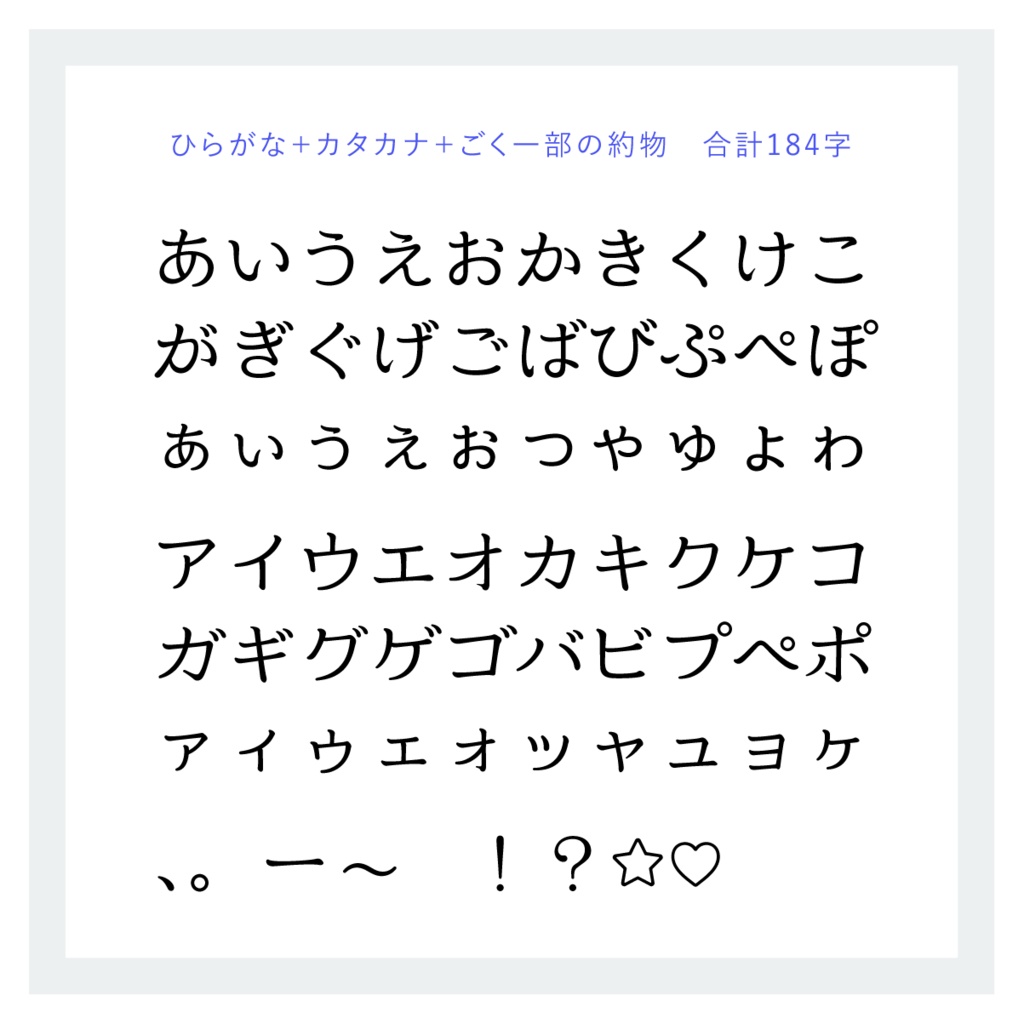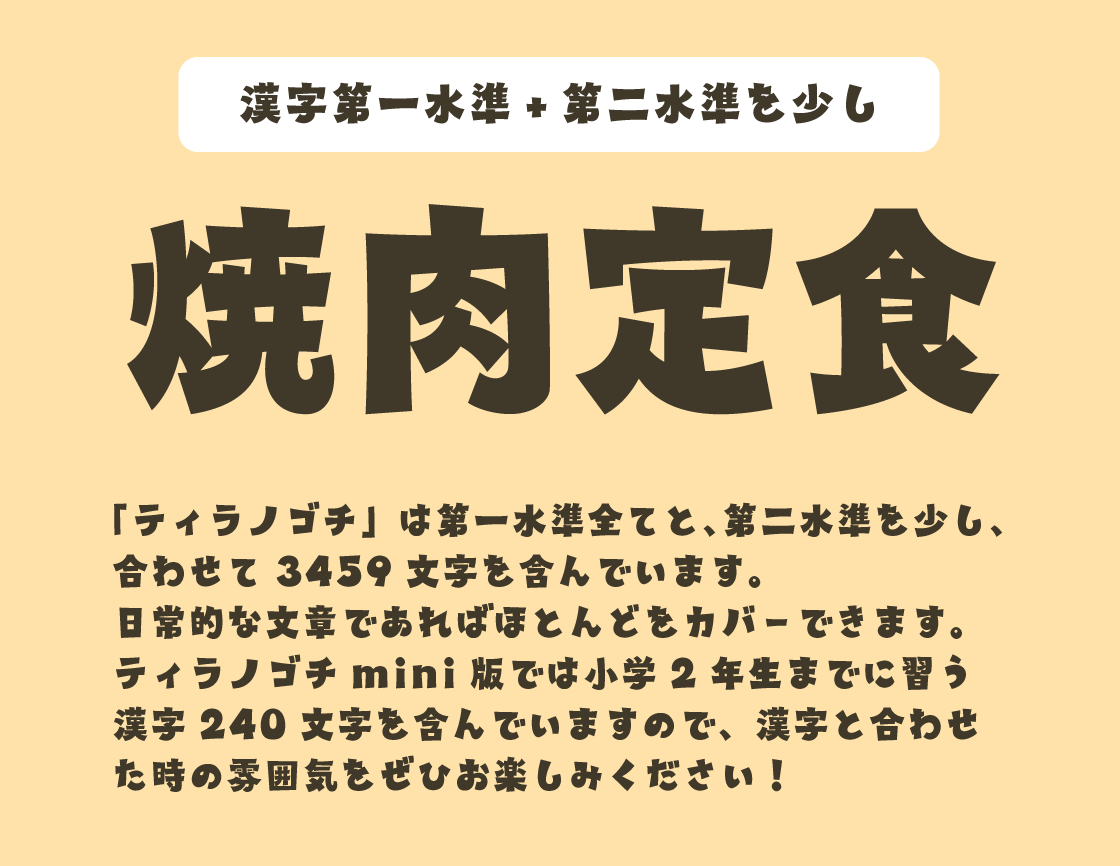
くすくすあめ
「くすくすあめ」は、昨年12月に公開されたばかりの比較的新しいフォントです。
シンプルながら手書きっぽさも感じられる丸ゴシック体フリーフォントとなっており、均一な線と優しい丸みが特徴で、やわらかな雰囲気を演出したいデザインに最適です。
スタイルに癖がないので、どのような場面でも使用しやすいフォントです。
| スタイル・ベース | 手書き風丸ゴシック |
| 収録内容 | ひらがな、カタカナ、漢字、数字、アルファベット、一部の記号 |
MPRばるーん
「MPRばるーん」は、M PLUS Rounded(M+)というオープンライセンスを使用したフォントです。今年の1月に公開されたばかりの新しいフォントとなっています。
幼稚園や保育園、学校だより、子ども向けの資料などにもぴったりなフォントです。風船の形は自動で決まるようです。
| スタイル・ベース | ポップ |
| 収録内容 | ひらがな、カタカナ、数字、アルファベット、一部の記号 |
はにはにフォント
「はにはにフォント」は、昨年8月に公開された手書きフォントです。ひらがな、カタカナ、数字、アルファベットが収録されています。フォントがとても可愛いので、漢字が含まれていないのが非常に残念です。
手紙風のデザイン、女性向けのランディングページ(クリエイティブ制作)にもぴったりで、個人的には手書きスタイルのなかでもイチオシのフォントです。
| スタイル・ベース | 手書き |
| 収録内容 | ひらがな、カタカナ、数字、アルファベット |
みそら明朝
「みそら明朝」は、「見やすさとかわいらしさ」を兼ね備えた明朝体フォントです。デザイン性と使いやすさのバランスが取れたスタイルとなっています。
| スタイル・ベース | 明朝 |
| 収録内容 | ひらがな、カタカナ、一部の約物・記号 |
りんごひめ(無料版)
「りんごひめ」は、レトロでキュートな雰囲気を持つシンプルかつデザイン性の高いフォントです。
無料版ではレギュラーウェイトのみが提供され、有料版にはボールドも含まれています。懐かしさと可愛らしさを演出したい場面に最適な書体です。
| スタイル・ベース | 手描き風レトロ |
| 収録内容 | ひらがな、一部記号 |
あおさぎ
「あおさぎ」は、デザイン性と実用性を兼ね備えた明朝体フォントです。豊富な文字数を収録しながら、商用利用可能で無料という特徴があります。
見出しやロゴデザインにも適しており、インパクトのある表現を可能にします。
| スタイル・ベース | 明朝 |
| 収録内容(無料版) | ひらがな、カタカナ、漢字、数字、アルファベット、記号、約物 |
ティラノゴチ(無料版)
「ティラノゴチ」は、やんちゃ小僧をイメージした、かわいらしさと力強さを兼ね備えたフォントです。遊び心のあるデザインで、個性的な表現を求める方に最適。
mini(無料)版は横書きのみとなっています。
| スタイル・ベース | 手書き |
| 収録内容(無料版) | ひらがな、カタカナ、漢字240文字 |
ぱぐのみんちょ(無料版)
「ぱぐのみんちょ」は、パグをモチーフにした愛嬌たっぷりの日本語フォントです。丸みを帯びた有機的なシルエットが特徴で、デザインにに温かみと可愛らしさを演出します。
mini(無料)版は横書き専用です。
| スタイル・ベース | 明朝 |
| 収録内容(無料版) | ひらがな、カタカナ、漢字80文字 |
にくまるフォント
「にくまるフォント」は、丸みを帯びた優しい印象の文字デザインが特徴です。ひらがなも漢字も柔らかな曲線で構成され、親しみやすさと可愛らしさを感じられます。
太めの字体で、温かみのある雰囲気を醸し出すのに適しています。細めより太めのフォントを探されている方にもぴったりです。
| スタイル・ベース | ベースはM+のためゴシック体に近い |
| 収録内容(無料版) | ひらがな、カタカナ、漢字、数字、アルファベット、記号 |
ふわふで
「ふわふで」は、やわらかい筆致が特徴の可愛らしい毛筆フォントです。
墨のにじみ感と丸みを帯びた文字形が、温かみのある和風デザインとなっていて、女性向けの和テイストな制作物に最適です。
| スタイル・ベース | 手書き |
| 収録内容(無料版) | ひらがな、カタカナ、数字、アルファベット |
ふわもこフォント
「ふわもこフォント」は、雲のような柔らかな印象の可愛らしい書体です。白抜きデザインが特徴的で、親しみやすさと高いデザイン性を兼ね備えています。
温かみのある雰囲気を演出するのに適したフォントです。
| スタイル・ベース | 手書き |
| 収録内容(無料版) | ひらがな、カタカナ、数字、アルファベット |
クラフト明朝
「クラフト明朝」は、手書き風の味わいある明朝体フリーフォントです。程よいかすれが特徴的で、温かみのある雰囲気を演出します。
第一水準漢字まで収録され、個人・商用利用も可能な実用性の高いフォントです。
| スタイル・ベース | 手書き |
| 収録内容(無料版) | ひらがな、カタカナ、漢字、数字、アルファベット、約物 |
錦的ポップ体
「錦的ポップ体」は、YouTubeなどの動画テロップにも最適なフリーフォントです。
実際に使用すると、かわいらしさと読みやすさが際立ちます。POPな雰囲気を演出したい場面におすすめのフォントです。
| スタイル・ベース | ポップ |
| 収録内容 | ひらがな、カタカナ、数字、アルファベット、一部の記号 |
解星デコール(Kaisei Decol)
「解星デコール」は、文字の先端に丸い「うろこ」が特徴的な日本語フォントです。Googleフォントで提供されており、商用・非商用を問わず無料で利用できます。ダウンロードすればMicrosoft WordやExcelなどでも使えます。
このフォントは優美さと可愛らしさを持ち合わせており、短い見出しや装飾的な目的に最適です。Kaisei Optiとの併用が推奨されています。
| スタイル・ベース | 明朝体 |
| 収録内容 | ひらがな、カタカナ、数字、アルファベット、記号 |
ZEN丸ゴシック
「Zen丸ゴシック」は、角の深い丸みが特徴的な柔らかな印象のサンセリフ体フォントです。こちらもGoogleフォントですので、商用・非商用問わず無料で使用可能です。
細めのウェイトでも読みやすく、様々なシーンで使いやすいデザインとなっています。かわいらしさとおしゃれさを兼ね備え、柔らかな雰囲気のコミュニケーションに適しています。
| スタイル・ベース | ゴシック |
| 収録内容 | ひらがな、カタカナ、漢字、数字、アルファベット、記号 |